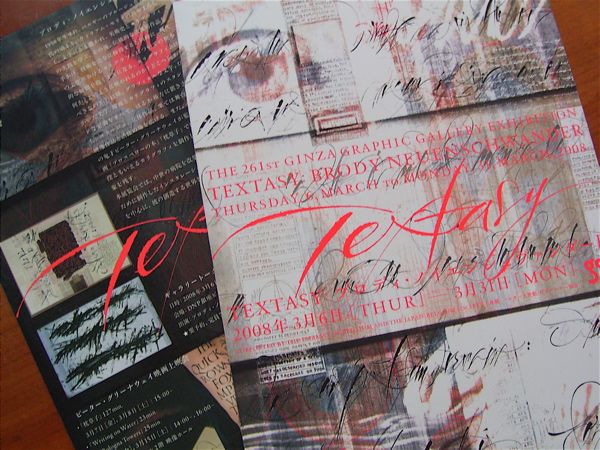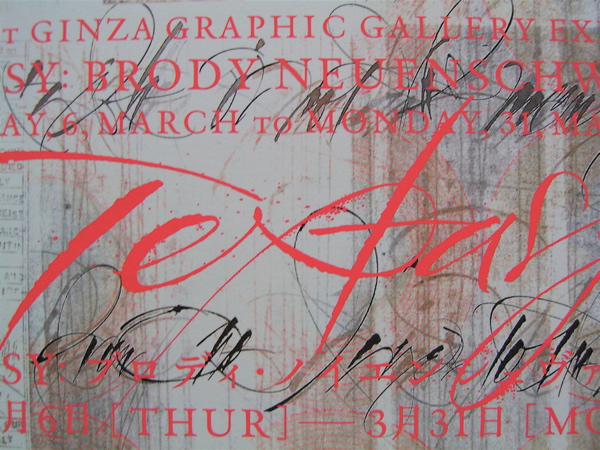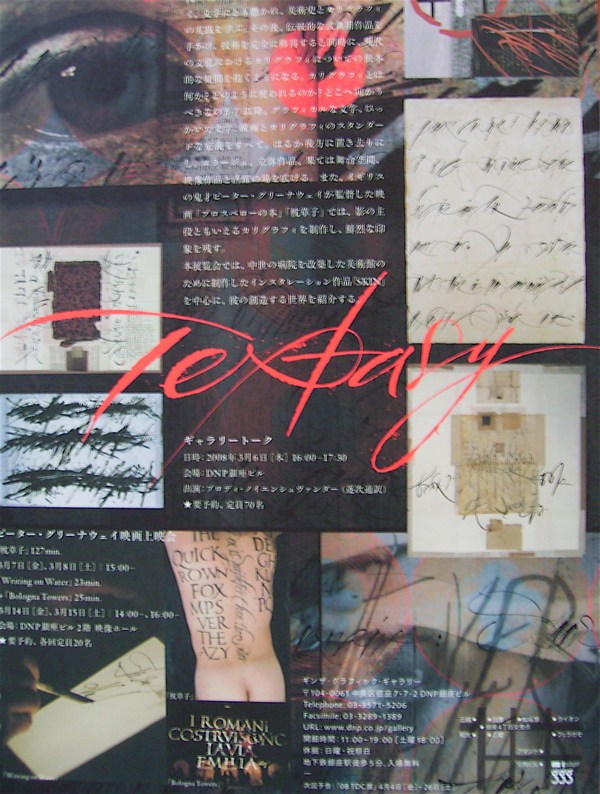
ブロディ・ノイエンシュヴァンダー展
今年3月6日から31日まで、ギンザグラフィックギャラリーにてBrody Neuenshwander氏による展覧会「TEXTASY」が開催されます。
カリグラファー、そしてテキストアーティストであるブロディ・ノイエンシュヴァンダーは、今や平面での表現に留まらず、立体作品、舞台空間、映像作品と活躍の場を広げています。ピーター・グリーナウェイ監督の映画においては、彼のカリグラフィーは映画の中の重要な要素として鮮烈な印象を残しました。今回の展覧会では、空間全体をカリグラフィーで埋め尽くす巨大なキャンバスと、Jeroen D’Hoe氏とのコラボレーション映像作品『SKIN』が展示されます。
このリーフレットは彼の文字の素晴らしさが良く表れていますね。手書き文字の表現力とカリグラフィーの可能性を日本でもっともっと高めていってくれたら、と期待がかかります。
ピーター・グリナウェイの映画「枕草子」の中でも、彼の文字は大きな役目を果たしました。今回のギンザの展示会では、ピーター・グリナウェイの映画上映会も予定されています。会場はいずれもDPN銀座ビル2F映像ホールです。
今上映中のピーターグリーナウェイの映画「レンブラントの夜警」にもブロディの文字が使われていますね。レンブラントの夜警
この映画気になっていたんですよね。Brodyの文字が使われているなのは知りませんでした。ますます気になる〜